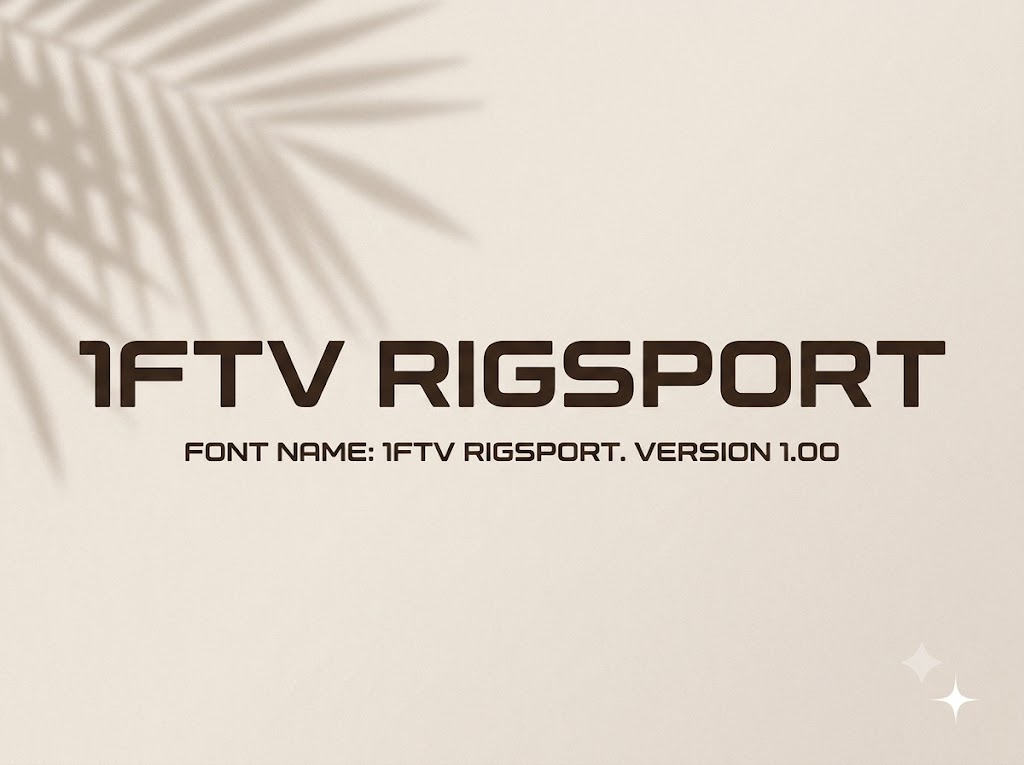
1FTV Rigsport
Trong giới thiết kế đồ họa hiện đại, xu hướng sử dụng các phông chữ dáng rộng (wide/extended font) đang ngày càng lên ngôi.
Những kiểu chữ mở rộng này luôn mang lại cảm giác bề thế, vững chãi và tạo ra một cú hích thị giác cực kỳ mạnh mẽ khi làm tiêu đề.
Nếu bạn đang tìm kiếm một bộ font chữ hầm hố, mang đậm tinh thần thể thao và công nghệ tương lai, thì font 1FTV Rigsport chính là lựa chọn không thể bỏ qua.
Giới thiệu về font 1FTV Rigsport
Font 1FTV Rigsport là một bộ chữ hiển thị không chân sở hữu phom dáng mở rộng theo chiều ngang đầy ấn tượng và độc đáo.
Được Việt hóa và chia sẻ rộng rãi bởi đội ngũ 1FTV, đây chắc chắn là công cụ đắc lực giúp nâng tầm các dự án sáng tạo của bạn tại Việt Nam.
Đặc điểm nổi bật của phong cách thiết kế Rigsport
Điểm đắt giá nhất của font 1FTV Rigsport nằm ở cấu trúc chữ vuông vắn kết hợp hài hòa với những đường bo góc ngoài nhẹ nhàng.
Phom dáng kéo giãn (extended) mang lại một cảm giác không gian rộng lớn, phóng khoáng, rất phù hợp với các chủ đề cần sự phá cách và nam tính.
Bộ font này hỗ trợ đầy đủ cả hệ thống chữ hoa lẫn chữ thường, tạo điều kiện thuận lợi cho các designer linh hoạt sắp xếp và căn chỉnh bố cục văn bản.
Nét chữ dày dặn, vững chãi giúp các khối từ khi xếp cạnh nhau luôn đạt được sự cân bằng tuyệt đối và chiếm trọn tâm trí người xem ngay từ cái nhìn đầu tiên.
Để phông chữ vận hành mượt mà trên hệ thống máy tính, phiên bản font 1FTV Rigsport đã trải qua quy trình xử lý thông số kỹ thuật vô cùng nghiêm ngặt.
Hệ thống khoảng cách chữ (kerning) được tinh chỉnh khoa học, giúp các ký tự khi đứng cạnh nhau luôn giữ được sự liền mạch và tính thẩm mỹ cao nhất.
Bên cạnh hệ thống chữ cái đồng bộ, font còn tích hợp đầy đủ dãy số từ 0-9 cùng hệ thống các ký tự đặc biệt, dấu câu thông dụng (1234567890.:,;'"(!?)+-*/=).
Bản Việt hóa này giúp các nhà sáng tạo nội dung hoàn toàn yên tâm thiết kế các văn bản tiếng Việt mà không lo gặp phải tình trạng nhảy font hay thiếu ký tự.
Hình ảnh demo thực tế của font 1FTV Rigsport
Để giúp bạn dễ dàng hình dung khả năng co giãn và hiển thị linh hoạt của phông chữ này trên các kích thước khác nhau, hãy cùng xem qua bảng mô phỏng từ file hệ thống:
Kích thước nhỏ (12pt – 24pt): Dù sở hữu phom dáng mở rộng, các nét chữ vuông vắn vẫn hiển thị rõ ràng, ngay ngắn và dễ đọc trên giao diện màn hình di động.
Kích thước lớn (36pt – 72pt): Đây là đất diễn lý tưởng nhất để font chữ phô diễn sự hầm hố, tạo hiệu ứng thị giác bứt phá cực mạnh cho các tiêu đề chính.
Ứng dụng của font Rigsport trong thiết kế đồ họa và làm video
Sở hữu nét cá tính mạnh mẽ và cấu trúc hình khối phóng khoáng, font 1FTV Rigsport mở ra không gian ứng dụng rộng lớn cho các dự án truyền thông:
Thiết kế Poster, Banner Thể thao và Gaming: Cực kỳ hoàn hảo cho các giải đấu esports, poster câu lạc bộ gym, fitness, đua xe thể thao hoặc các sự kiện vận động mạnh.
Làm tiêu đề video ngắn (TikTok, Reels, Shorts): Giúp các từ khóa chính hay tiêu đề mở đầu video trở nên vô cùng bắt mắt, kích thích thị giác và giữ chân người xem.
Ảnh thu nhỏ YouTube (Thumbnail): Đặc biệt hiệu quả với các kênh thuộc chủ đề công nghệ, đánh giá xe, đồ điện tử hoặc các nội dung hành động, khám phá đời sống.
Nhận diện thương hiệu phong cách đường phố: Phù hợp làm logo dạng chữ khối, biểu ngữ quảng cáo hoặc thiết kế bao bì cho các thương hiệu thời trang streetwear cá tính.